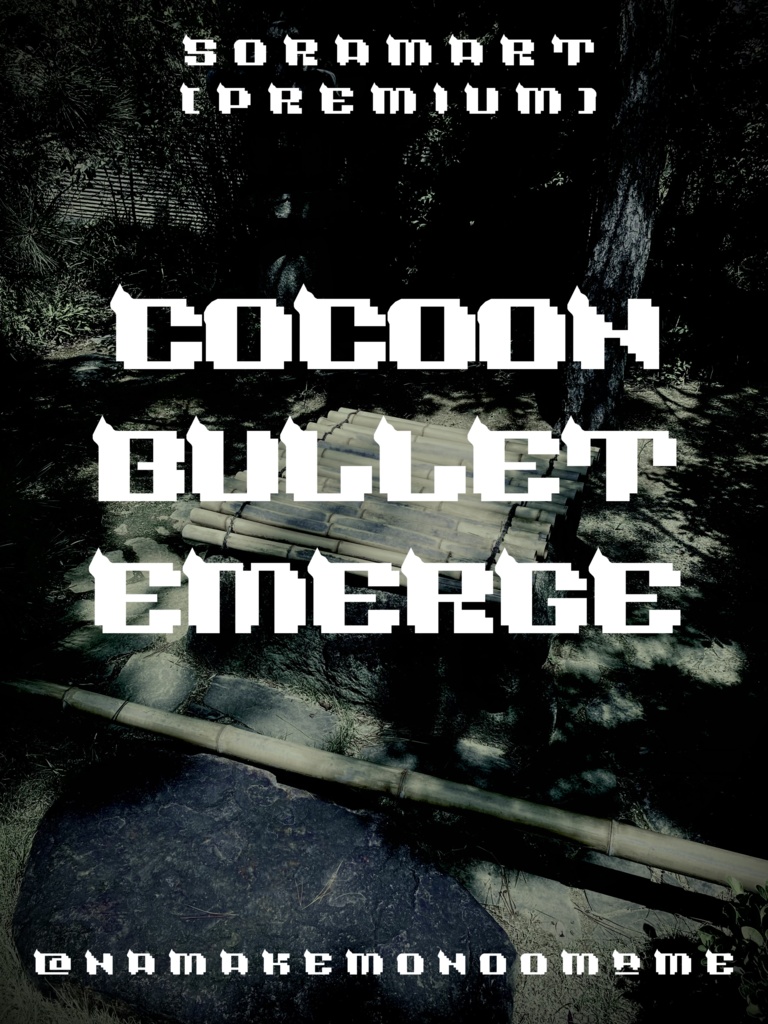
そらマートフォントデータ”Cocoon Bullet Emerge”Digital2,500 JPYAdd to CartBuy a GiftAbout Gift離れてみると ”丸み” を感じるドット調フォント "Cocoon Bullet" です。 「TrueTypeフォントファイル」という形式です。 ダウンロードした後、Zipファイル内のデータをインストールしてお使いください。 このフォントは商用利用可となっております。 お客様の制作・創作活動のお役に立てれば幸いです。 ※使用上の注意事項などは、添付のReadmeをお読みください。 ※このフォントは、有料販売専用商品です。そらマートVisit FANBOX!Fontsフォントデータ”RANMMA Drive”そらマート0 JPYFontsフォントデータ”Dandy Laser Max”そらマート2,500 JPYFontsフォントデータ”Dandy Laser”そらマート2,500 JPYFontsフォントデータ”Bubblegum Beat”そらマート2,500 JPYFontsフォントデータ”Caltrop Serif LLL”そらマート2,500 JPYFontsフォントデータ”Caltrop Serif LL”そらマート2,500 JPYFontsフォントデータ”Caltrop Serif”そらマート2,500 JPYFontsフォントデータ”Tonik Crate Super Long”そらマート2,500 JPYFontsフォントデータ”Dot Eat Bug Acid”そらマート2,500 JPYFontsフォントデータ”Dot Eat Bug Mild”そらマート2,500 JPYFontsフォントデータ”Dot Eat Bug”そらマート2,500 JPYFontsフォントデータ”Solid Voltage Strike”そらマート2,500 JPYFontsフォントデータ”Solid Voltage”そらマート2,500 JPYFontsフォントデータ”Henge Edge Rock”そらマート2,500 JPYFontsフォントデータ”Henge Edge Tall”そらマート0 JPYFontsフォントデータ”Henge Edge”そらマート0 JPYFontsフォントデータ”Chisel Stroke Wide”そらマート2,500 JPYFontsフォントデータ”Chisel Stroke”そらマート2,500 JPYFontsフォントデータ”Crushed Can Serif Empty”そらマート2,500 JPYFontsフォントデータ”Crushed Can Serif Wide”そらマート2,500 JPYSee More